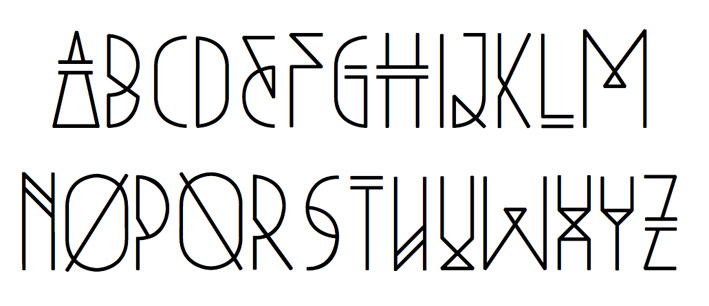
Una tipografía con aires de Art Deco por su extensa geometría, perfecta para logotipos e ilustraciones.
A typography with an Art Deco feeling for its extensive geometry, perfect for logos and illustrations.